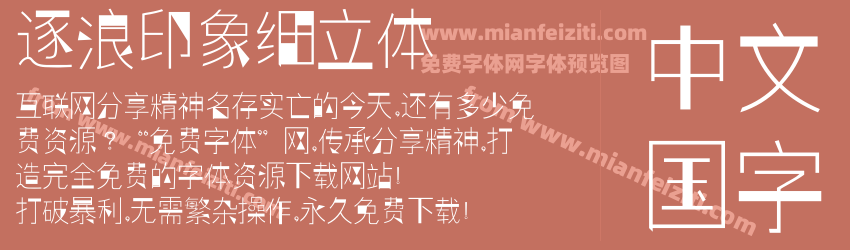
逐浪印象细立体
字体名称: 逐浪印象细立体
字体品牌: 逐浪
这是一款简体字库,基于GB18030标准。
立体主义(Cubism)是西方现代艺术史上的一个运动和流派,又译为立方主义,1908年始于法国。立体主义的艺术家追求碎裂、解析、重新组合的形式,形成分离的画面,以许多组合的碎片型态为艺术家们所要展现的目标。艺术家以许多的角度来描写对象物,将其置于同一个画面之中,以此来表达对象物最为完整的形象。
逐浪字库的团队成员,以印象主义切入,创造了独到的字库体验。
它如三角台灯,照亮下面的丽人、生活与家。如字:流、琦
它如远方的山,又如父爱如山,在字的中间形成重心,如字:离
它是实验室的小烧瓶,俏皮的液体在不断上升-如字:潮。
它是方正厚实的几何之美,值得信任-如字:屋。
它有着红与黑、方与圆的对比-如字:蹦。
它向不规划挑战-如字:依、新、柳
它能在压抑的类比中脱颖而出-如字:熙。
它比别人更加多姿多彩,却又无感累赘-如字:柳
它如同绅士,总是身边有丽人或是配合得体-如字:酥
它如同毕加索笔下的几何造型,虽然看似简单,却又别具风格。
看似堆砌,却又有几何之美。
将西方的几何美学与东方的立体造型结合,
创造出独特的美,
使书写的意境得到最大的化进升。
本款“逐浪印象细立体”是一款书写很新颖的字体,字体大方,适合各种设计作品使用!欢迎下载!